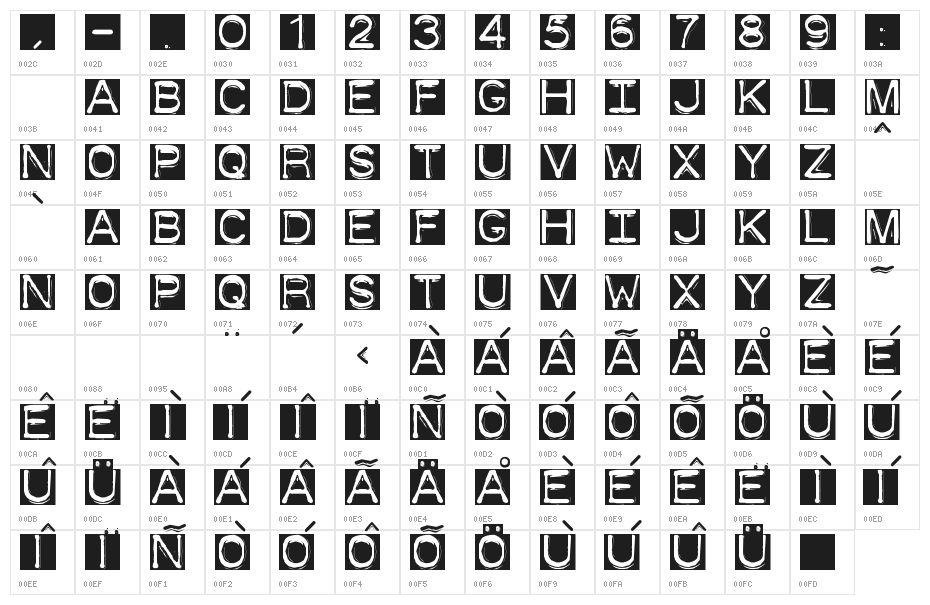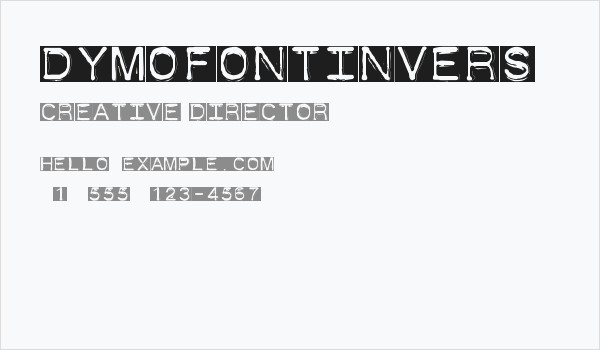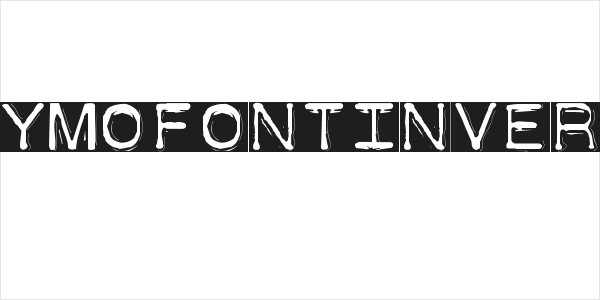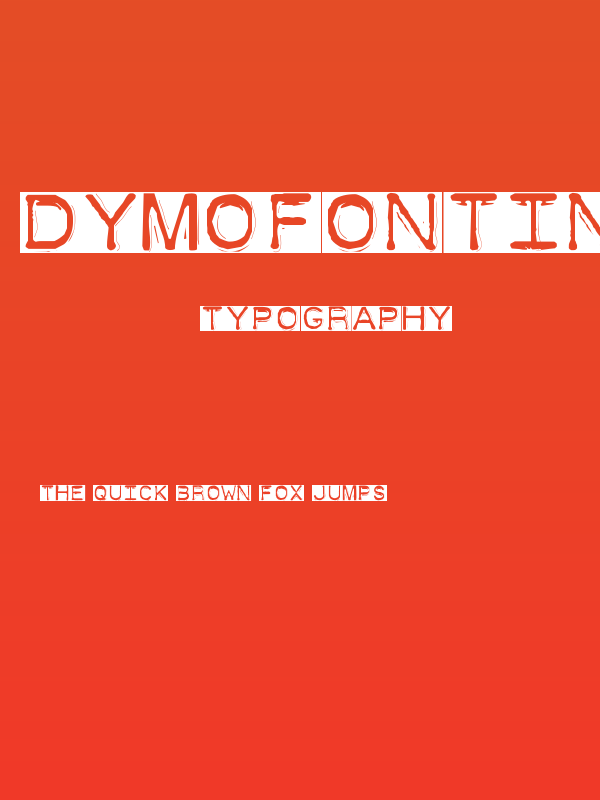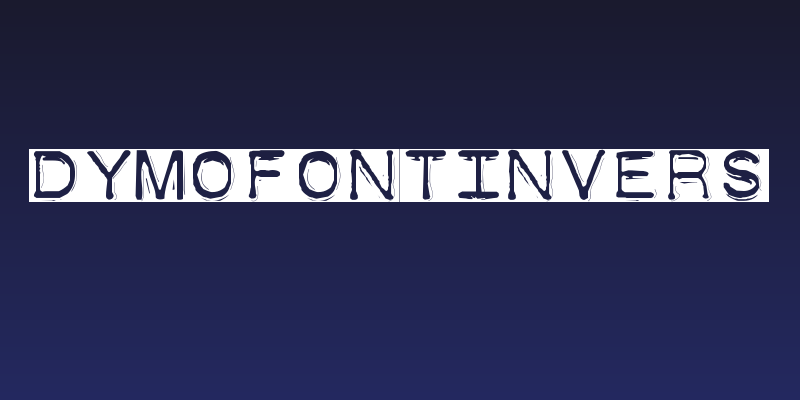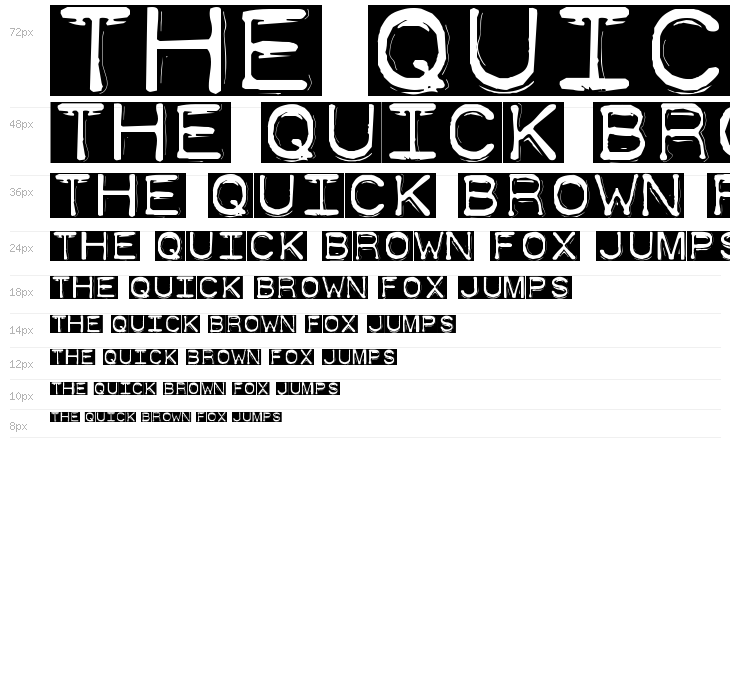
DymoFontInvers Font
✎ Decorative
| Kategorien | Decorative |
| Gesamtstil | Vintage |
| Vorgeschlagene Projekte | Ideal for vintage-themed designs, labels, packaging, posters, and branding projects that require a bold, standout typeface. |